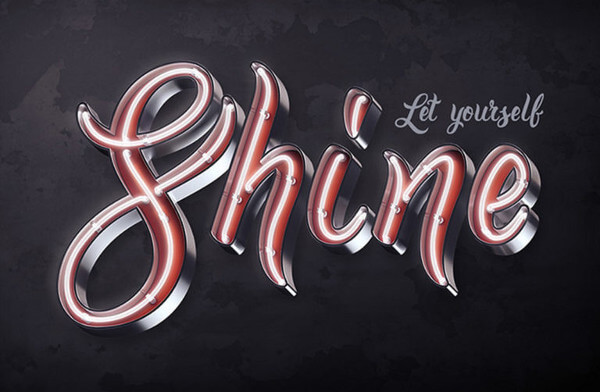
【2018年おすすめフリーフォント19選】最新トレンドからヴィンテージ風まで
写真やイラストにはテキスト数千語分の表現力があります。しかし、画像のみでデザインすることはできません。言葉と画像の両方があってこそ、読み手に正確なメッセージを伝えることができるのです。
この記事では、2018年にトライしたいおすすめのフリーフォントをご紹介します!
Vhiena
Quantum
ヴィンテージ風のロゴを作成するとします。そんな時はVhienaのようなノスタルジックなフォントを試してみてください。このフォントには7パターンあり、組み合わせて使うことができます。
あるいは、超現代的な雰囲気なロゴを依頼されたとします。その場合は、大文字が未来的な魅力を持つQuantumのようなフォントで仕上げることができます。
現代のタイポグラフィにはあらゆる可能性があります。Spirited Font Setのようなエレガントなカリグラフィーフォントから、Barking Catのような素朴なものまで、形やスタイルやデザインで書体を選ぶことができます。
Spirited Font Set
Barking Cat
2018年のトレンドはジオメトリーとハイテクです。フォントの最新トレンドは、Pikolo Block Alt、Celebration、Kumu、Natureあたりが要チェックです。これらのフリーフォントは今年のトレンドを着実に掴んでいます。
Pikolo Block AltとCelebrationは、共通点が多いフォントです。ラインアートの美しさがあり、大文字・小文字・数字・記号・一般的な合字も入っています。ロゴ、タイトル、バナーなどを作成する時に使ってみましょう。
Pikolo Block Alt
Celebration
Kumuの文字は、大きめのドットをバランスよく組み合わせて作られています。フォントはやや素朴な感じですが、ブルータリズムのデザインを完成するのには理想的です。
Kumu
Natureは幾何学的な線とエレガントなフォームを巧みに組み合わせた、華やかで洗練されたフォントです。近代的なデザインに最適です。大文字と小文字の両方が使えます。
Nature
芸術性のあるフォント
最新トレンドに関心がなければ、芸術性の高いフォントやオリジナリティのあるフォントはどうでしょうか。
芸術性の高いフォントは、カリスマ性と創造性のある雰囲気を作り出します。Petals、Naive Color Font、Crush Oneがオススメです。
Petalsはその名の通り、「花びら」の表現が特徴的なフォント。バラの美しいディテールがほどこされており、文字の一つ一つに素敵な女性的オーラがあります。
Petals
Naive Color Fontは大胆で、キャッチーです。その幾何学的な雰囲気が持つ圧倒的な存在感は清々しいほどです。大文字、数字、および基本的な句読点のみ使用できます。
Naive Color Font
Crash Oneは、素早く気まぐれな雰囲気です。遊び心のあるカリスマが滲み出てきます。
Crash One
オリジナリティのあるフォント
オリジナリティのあるフォントは、実験的な書体と珍しい見た目で、見る人を驚かせます。
面白いフォントを2つご紹介します。FixerとHawaiian Kidsです。
Fixer
Hawaiian Kids
Webフォント
2009年にWOFF(Web Open Font Format)が開発され、ウェブデザインにとって2009年は画期的な年となりました。WOFFは、ウェブサイトのためのタイポグラフィのビジョンを変えました。
Coral Reef Fontは、多種多様な印刷プロジェクトに最適です。 WOFFなのでWebアプリケーションで使用でき、どんなデバイスでも見栄えが良くなります。
Coral Reef Font
もう1つの大きな利点は、Cocoなどのフォントに使用できるコンバーターが数多くあることです。この美しい書体は絶妙な字形を持ち、標準的なOTFで利用できます。エレガントなデザインを仕上げるのに理想的です。
Coco
PSDとワイヤーフレーミングフォント
次に紹介する2種類のフォントは他のフォントとは一線を画しており、独特です。
PSDフォントは驚くほど芸術的であるのに対して、ワイヤーフレーミングフォントは極度に単純化されています。
PSDフォントは、何の変哲もない普通の見出しを芸術作品に変えてしまいます。Bright Calligraphy PSD Typeface、Neon、Adan Fontを見てみましょう。
Bright Calligraphy PSD Typeface
Neon
Adan Font
ワイヤーフレーミング用のフリーフォントは、Lipsumを連想させるニュートラルなフォントです。プロトタイプ作成用であったり、見出しやテキストの範囲を明らかにするために使用されます。
Flow by Dan Ross